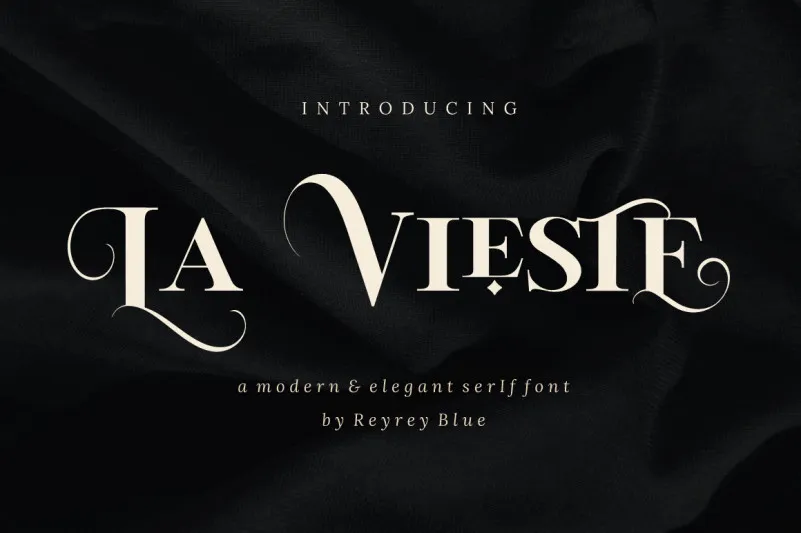
La Vieste Font – Download Grátis
La Vieste é uma fonte serif elegante criada por ReyreyBlue para designers e profissionais que valorizam elegância e sofisticação em seus projetos digitais. Com traços firmes, essa fonte adquire um toque distinto e confiante, tornando-a ideal não apenas para títulos de marca ou assinaturas, mas também para cartões de casamento, campanhas promocionais, embalagens de produtos e qualquer outro requisito gráfico que exigir uma atmosfera sofisticada. Suas linhas suaves e harmoniosas criam um impacto visual envolvente em suas criações, tornando La Vieste não apenas uma escolha perfeita para designers digitais atentos ao detalhe, mas também uma fonte indispensável para a gama de projetos onde a elegância se transforma em realidade visível.